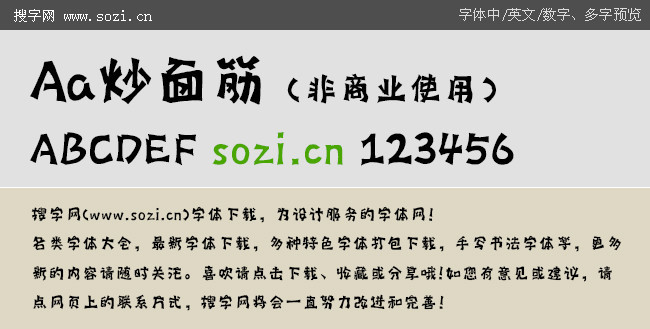
Aa炒面筋
搜字網(wǎng)給大家提供一款A(yù)a炒面筋(非商業(yè)使用)字體下載,該字體是一款不錯的卡通藝術(shù)字體,這款字體筆觸較為粗實,字形夸張,充滿童趣。適合書裝設(shè)計、包裝設(shè)計、海報設(shè)計等應(yīng)用(此字體為個人非商用版,商用可以聯(lián)系QQ:1006760504)。